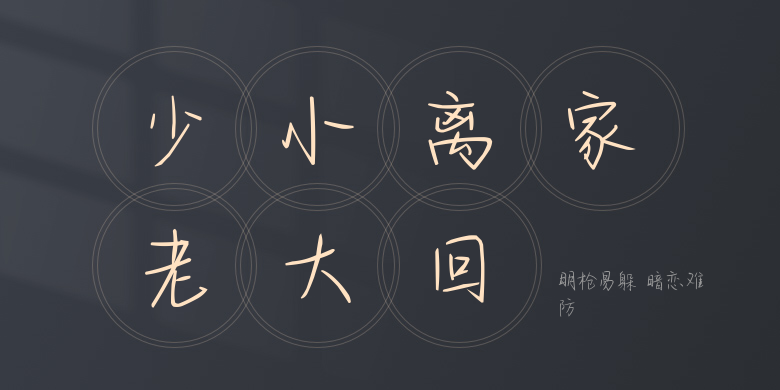
明枪易躲 暗恋难防
明枪易躲 暗恋难防,这款字体结构工整、笔画清晰,兼顾美观与易读性,适用于标题、正文、海报、包装、LOGO 等多种场景。字形优雅稳定,风格百搭耐看,适配日常排版与创意设计,让文字呈现更舒适、更具质感。明枪易躲 暗恋难防一笔一画,皆是细节,以均衡的比例、流畅的线条打造舒适视觉体验,字形端正大气,风格简约现代。无论是商业设计、品牌宣传还是日常排版,都能轻松驾驭,让文字更有格调与力量。明枪易躲 暗恋难防字体下载。